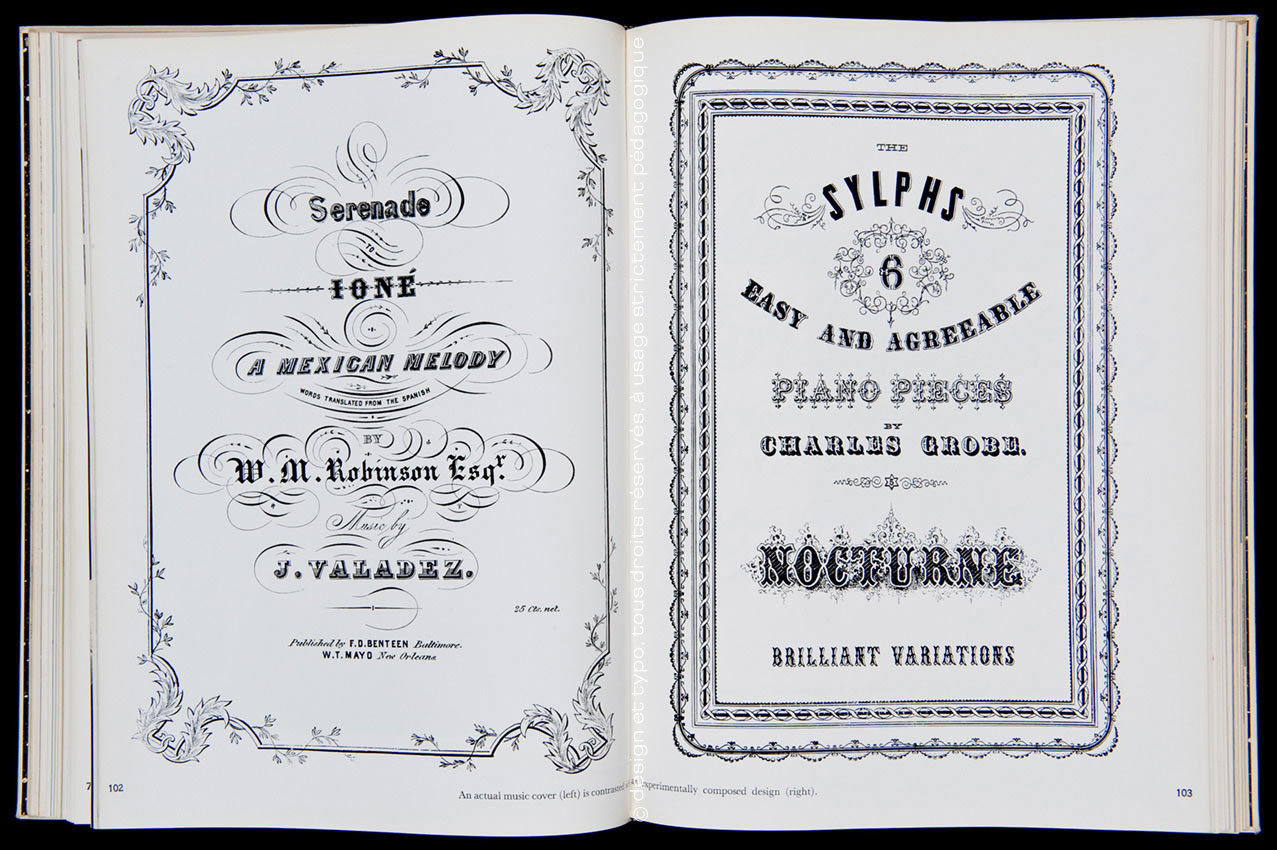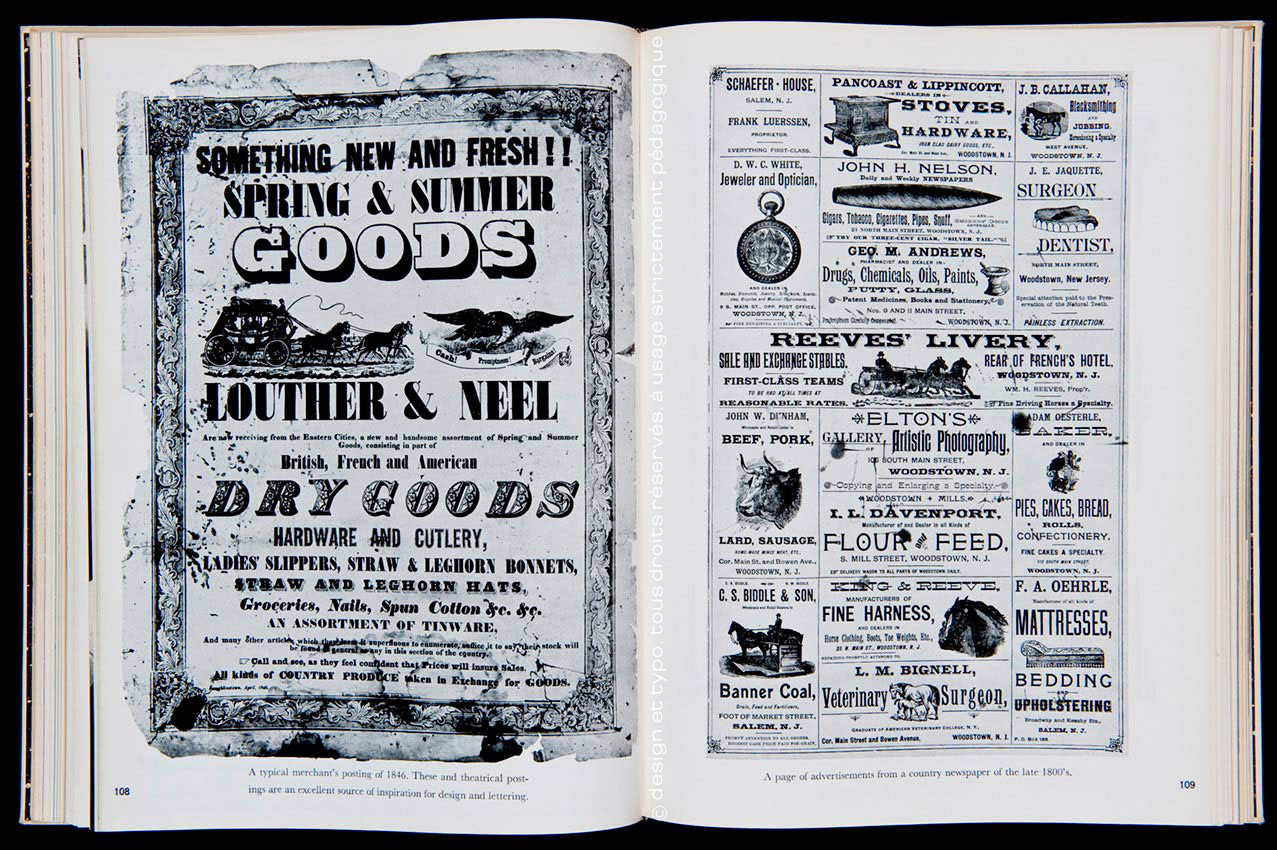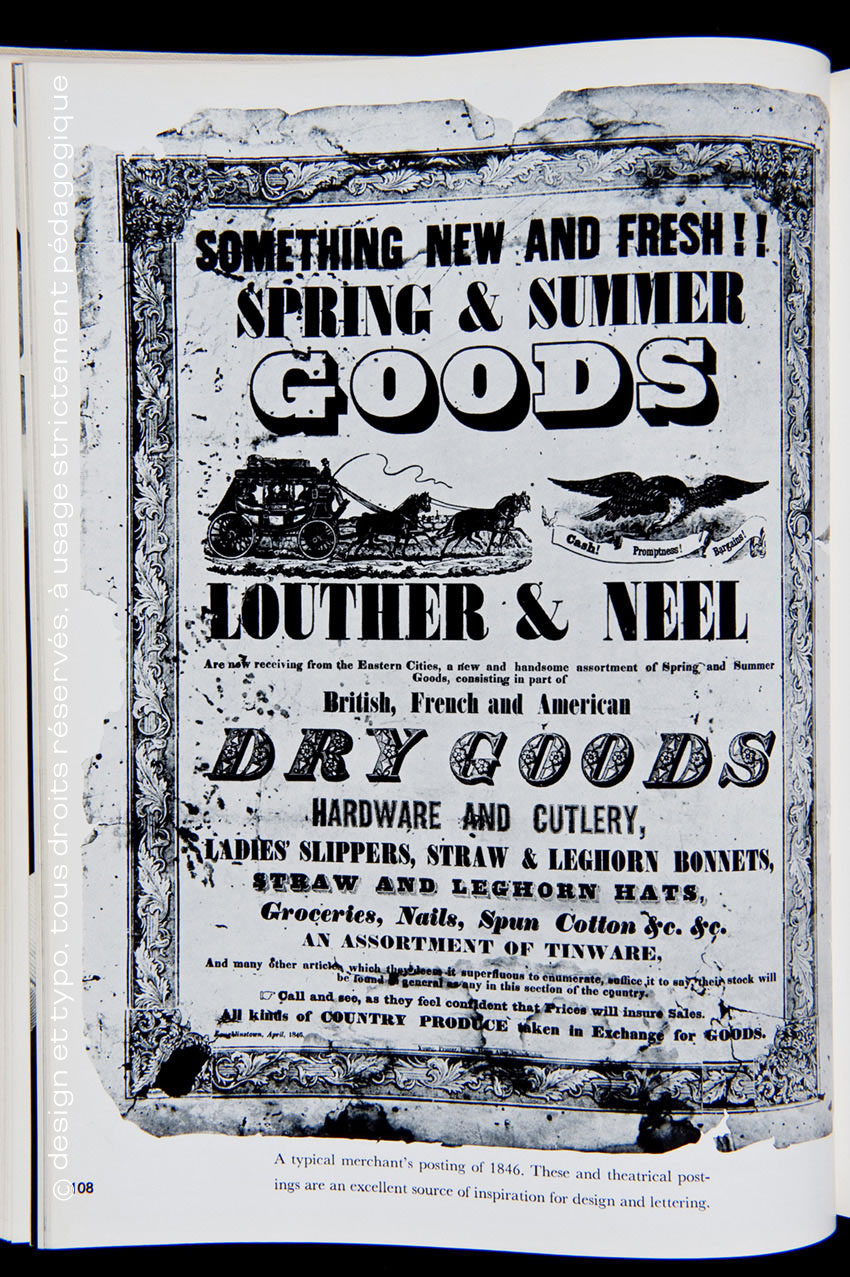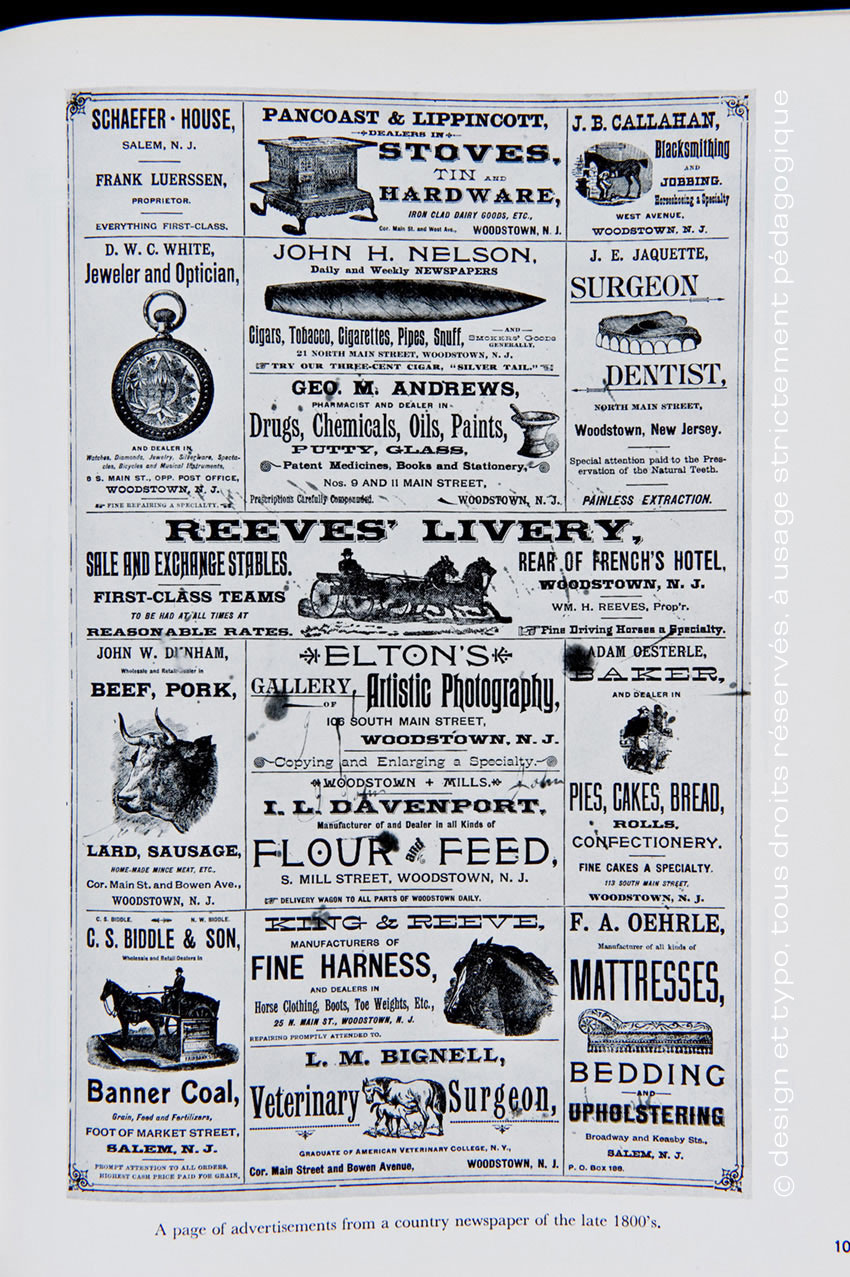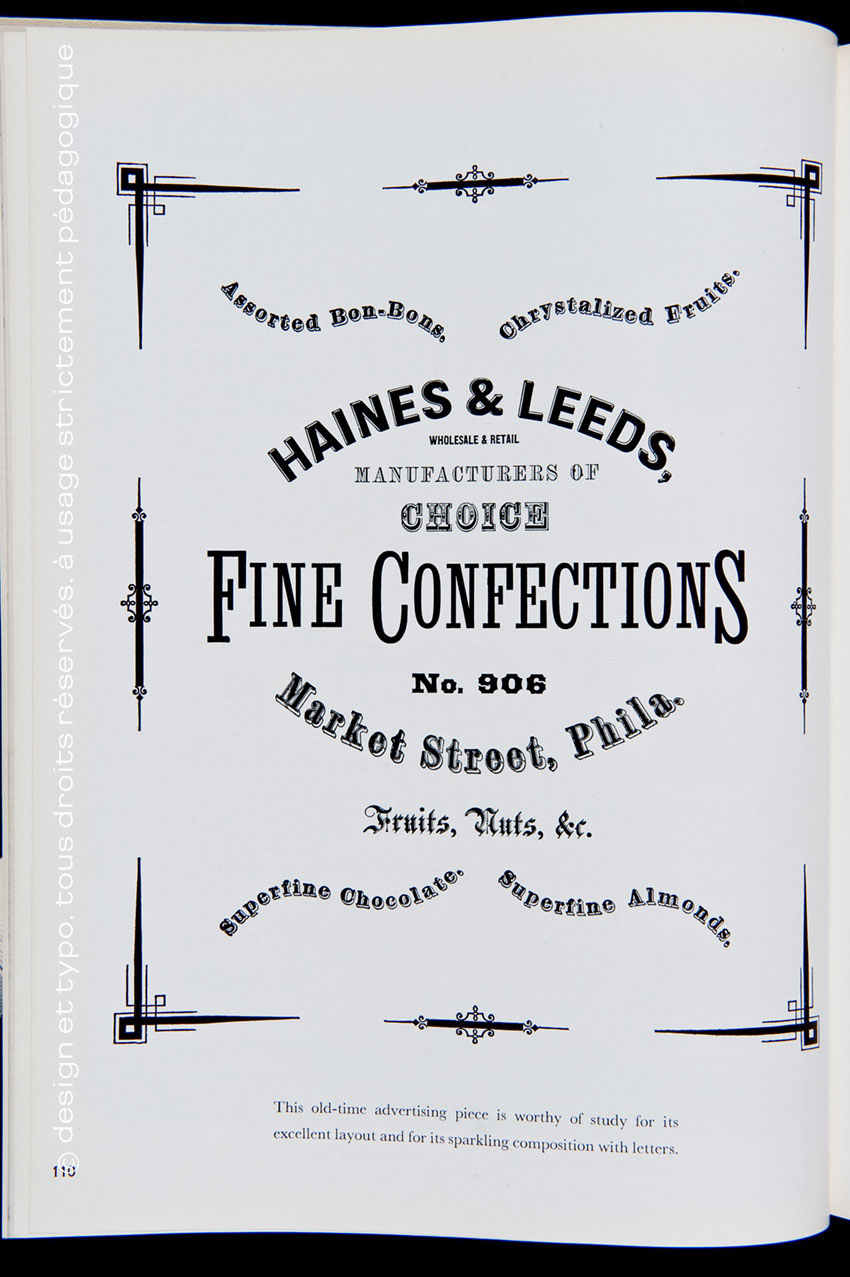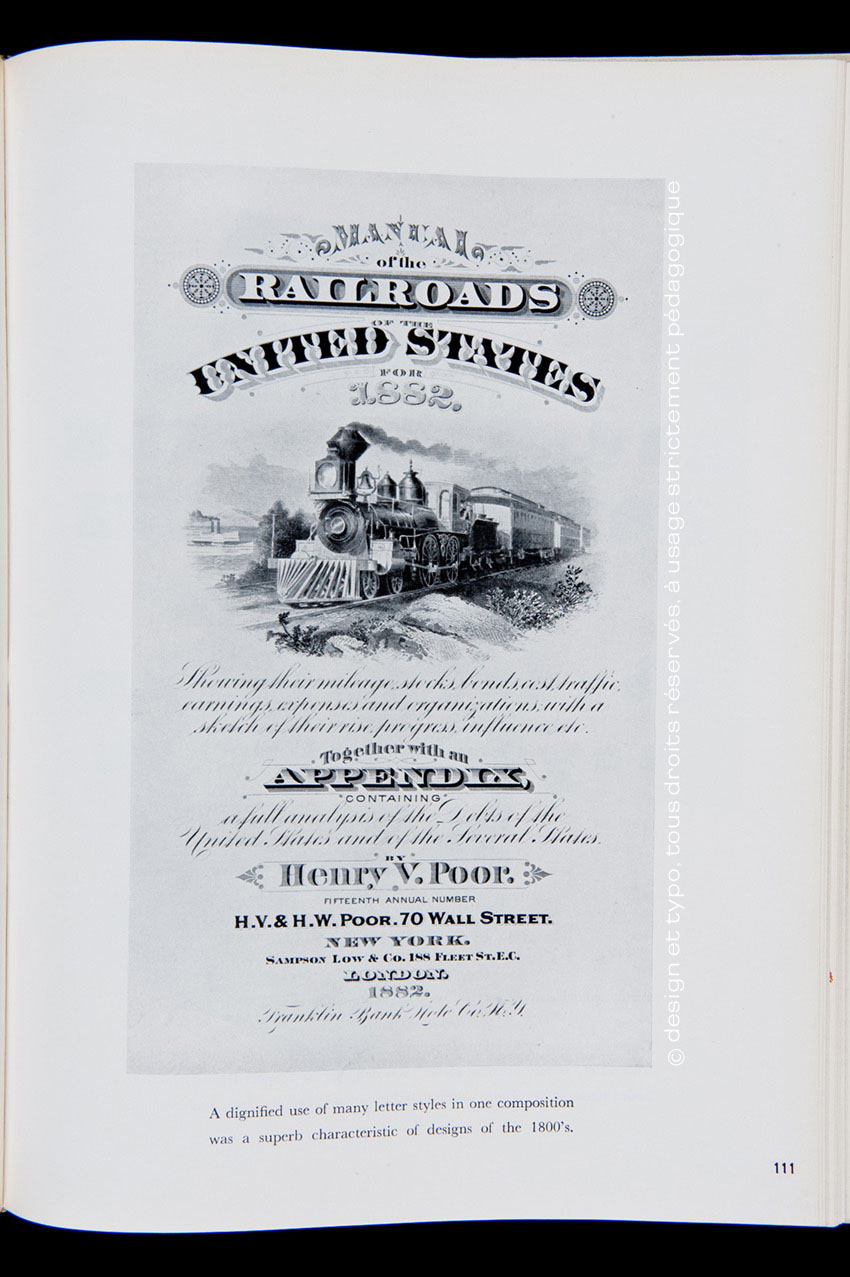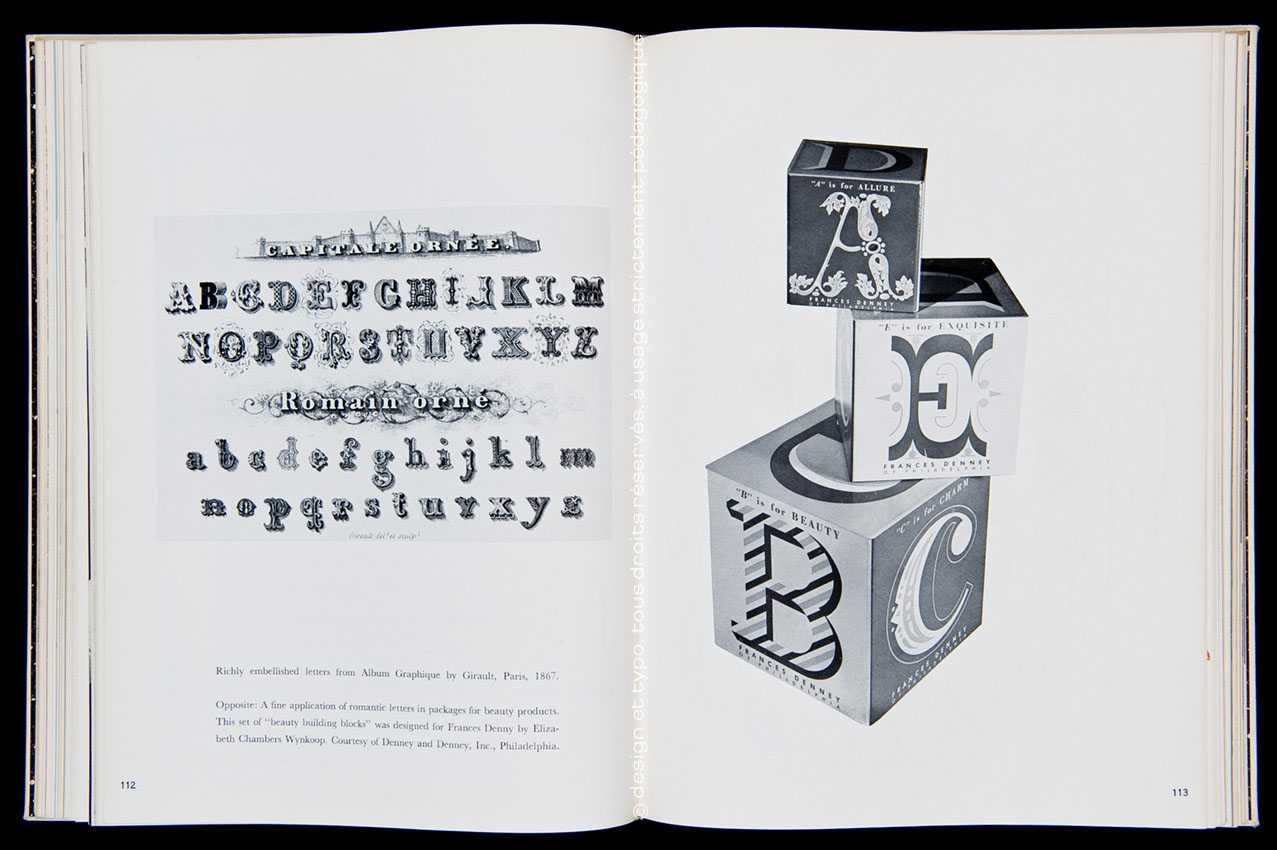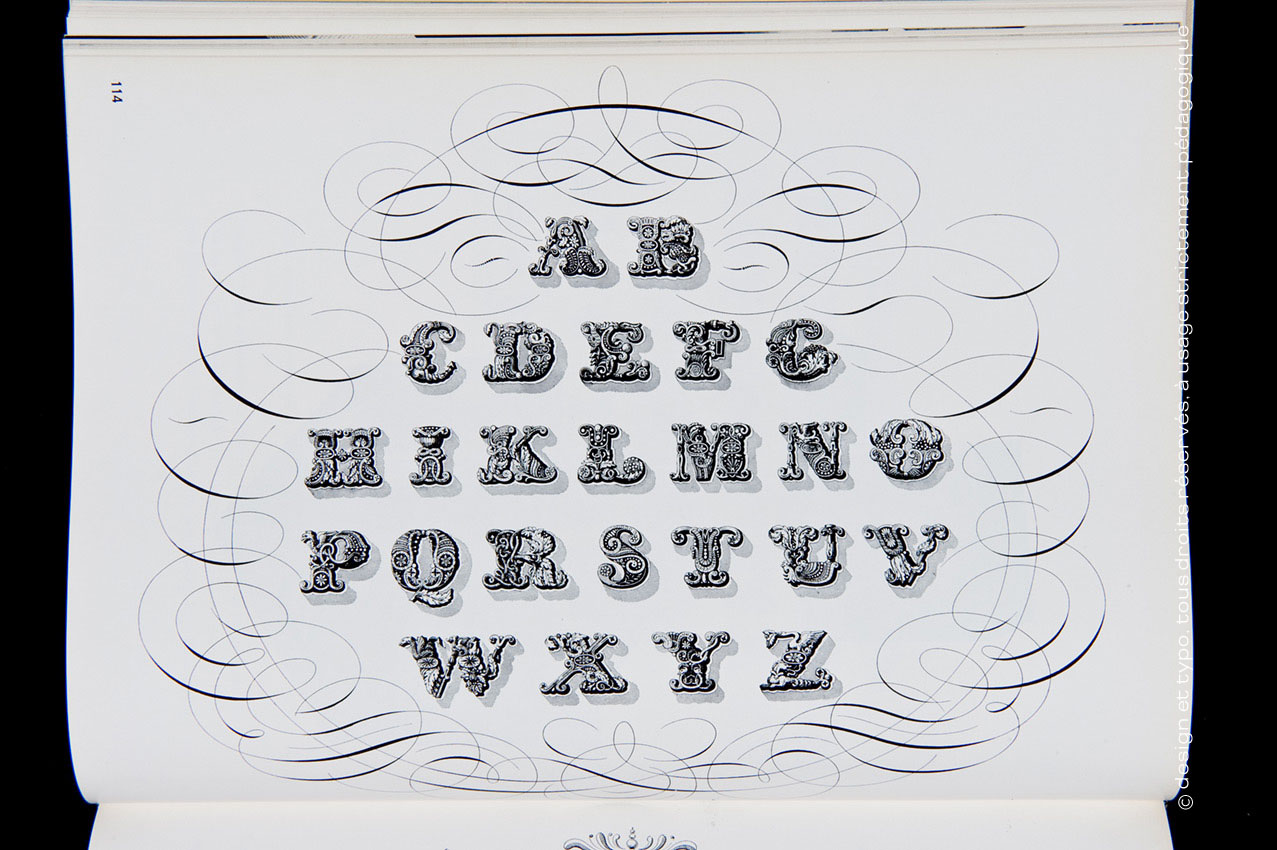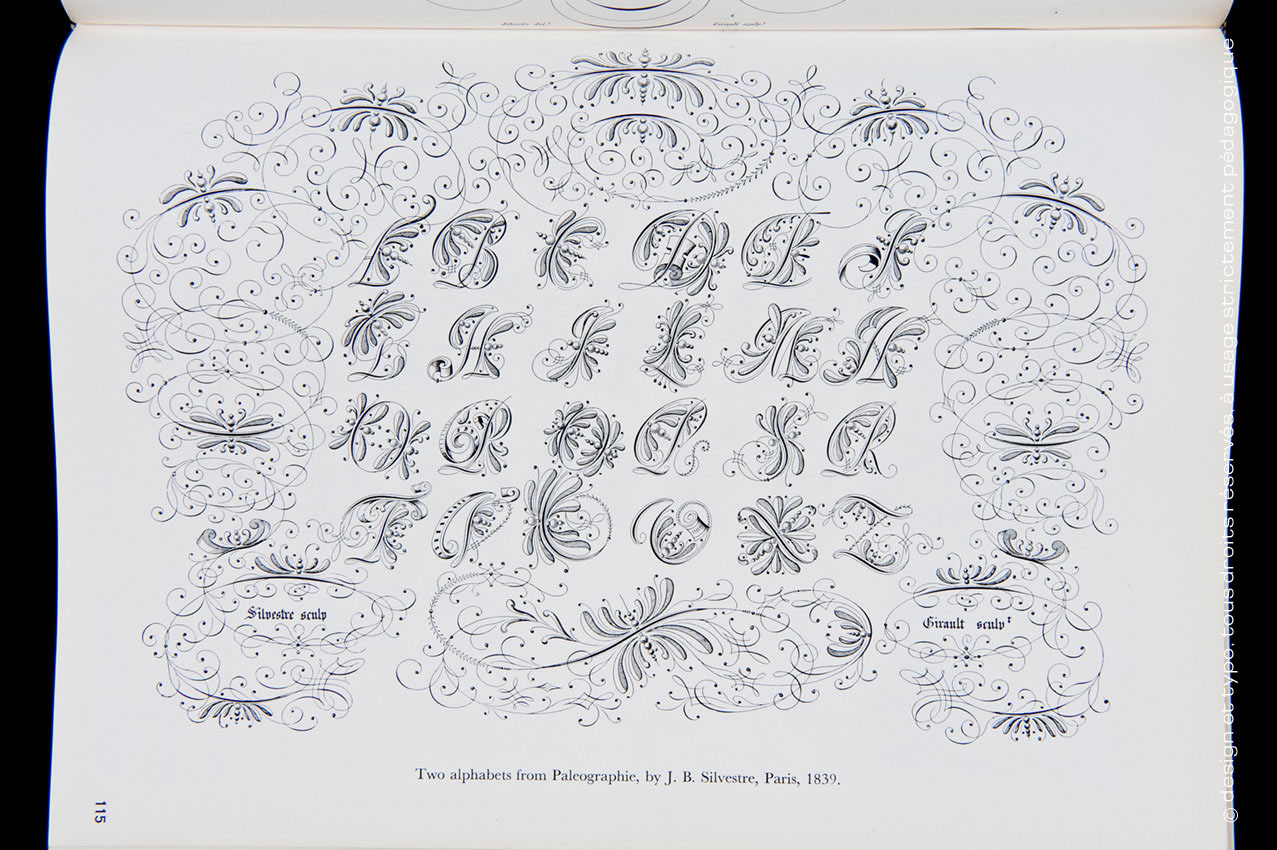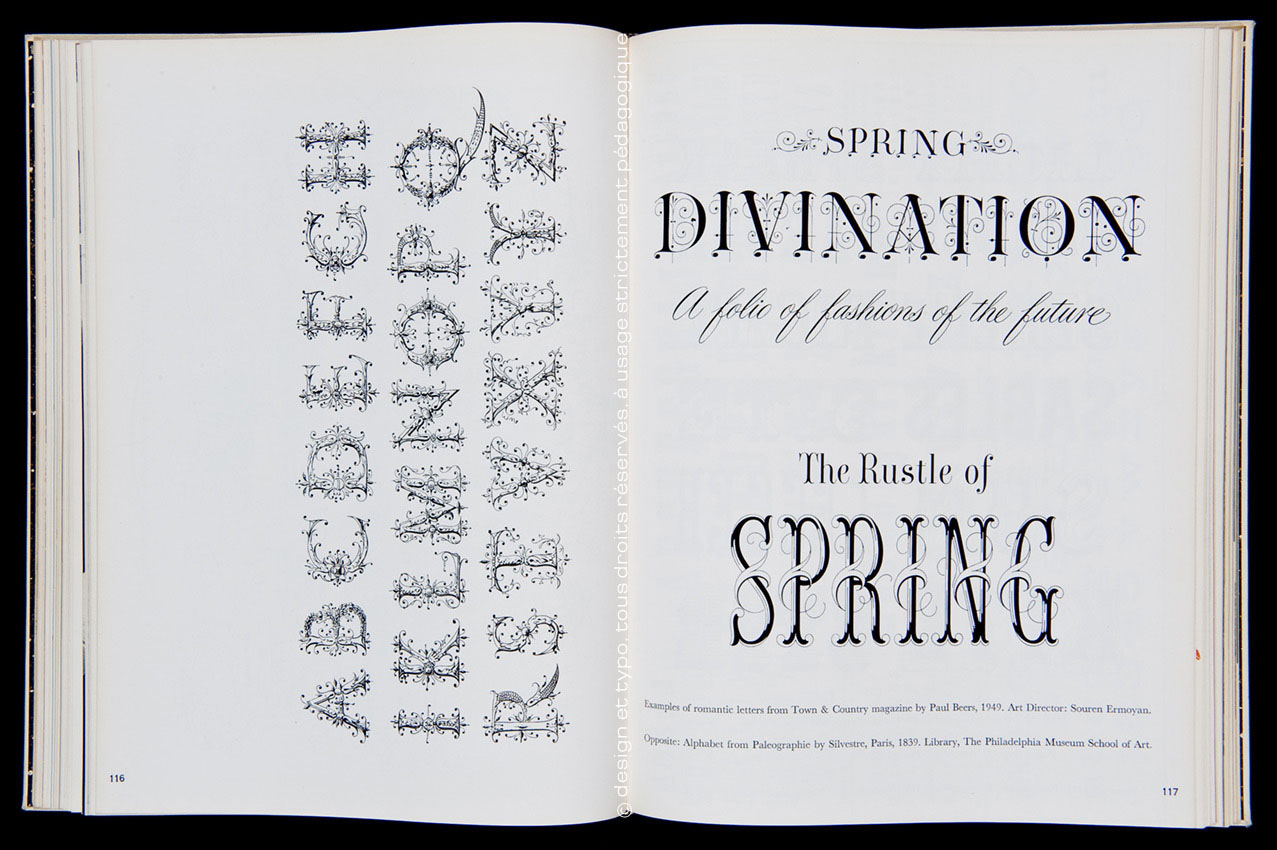
Typographie anglosaxonne et classification selon Raymond A.Ballinger (3/4)
Typography and classification by Raymond A.Ballinger
Nous entrons là dans ce que Raymond A.Ballinger appelle la typographie Romantique. Un manière pour Ballinger de souligner l’importance du choix des caractères selon le message à délivrer. De montrer aussi une méthode.
Si Romantique veut dire sentimental, nostalgique, oui les pages de publicités qu’il nous montre en témoignent à plus d’un égard. En premier lieu la multiplication des polices dans le champ de la communication marchande. Certaines des Réclames comptent plus de 15 polices par page. Sortes de catalogues de caractères pour imprimeur en mal de client.
Est-ce là un signe, un symptôme de romantisme… bavarde dirai-je cette clause de style. Mais Ballinger en choisissant minutieusement ses documents nous pointe déjà la question essentielle des moyens dont dispose le graphiste, le typographe pour communiquer des messages publicitaires. Et son inventaire s’il ressemble à celui de Jacques Prévert, n’en est pas moins une sorte de méthode du: ce qu’il faut faire ou pas faire pour être lu et pour séduire. Il nous en administre la preuve par le creux, le négatif, la mécréance et la parlote typographique.
Et on comprend d’avance alors que ce qui nous touchera, ce qui aura une chance de nous séduire, viendra de l’épure, de la simplicité prônée par un Massimo Vignelli, de l’élégance administrée par Herb Lubalin. Ou même, et bien plus tôt par Bradbury Thompson et Alvin Lustig. La multiplication des caractères «Saloon» façon Western nous montre également cette nostalgie des américains pour leur jeune passé qui n’arrive pas à outre-passer l’époque de la conquête de l’ouest.
Et là encore curieusement c’est la calligraphie, et les sociétés de calligraphie qui essaiment aux US qui va leur permettre de revenir vers les fondamentaux du graphisme. Herb Lubalin, et bien d’autres graphistes avaient choisi cette «filière» pour faire leur classes. Et l’on sait ce qu’il en est advenu. C’est dire qu’il n’est point besoin de sortir du Bauhaus pour comprendre les codes de l’élégance, les contrastes, les valeurs de blanc et noir, le rythme etc. La maîtrise du tracé calligraphique permet la même pédagogie et d’arriver à des résultats similaires.